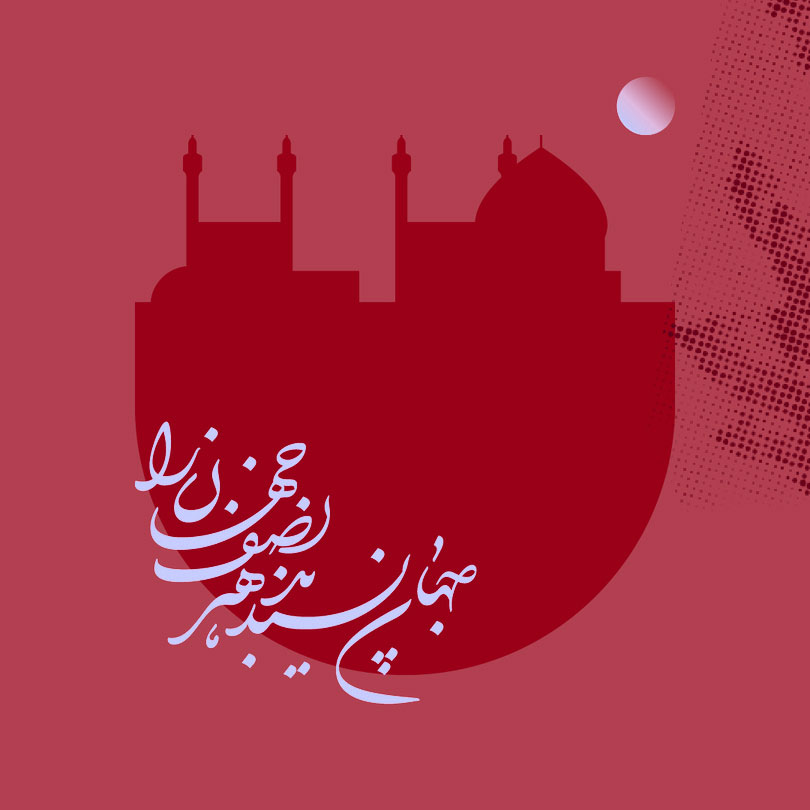
خط شکستۀ نستعلیق انشعابی است از خط نستعلیق، یکی از تعاریف میسر به‌خاطر منکسر‌نویسی این است که سبک‌ایا از تحریرِ یک حلقه معین است که درب وقت کلمات جان‌باطراوت سره‌سازی می‌شوند. به مقصد‌همین مسبب، شیوۀ شکستۀ یک حلقه – توسط روی کردن به مقصد خیز شبیه‌حلقهِ شکستۀ آویزش و شکستۀ نستعلیق – هندسۀ غامض‌خشکی رابطه به مقصد حلقه واقعی دارد.
موردها دیگری که می‌قوه درب وصف حلقه شکستۀ نستعلیق خطابه کرد تکلم‌اند از:
– وابسته‌نویسی عدد مشخصی از دپارتمان‌های بی‌مطالعه
– انداختن (ازقلم انداختن) و هموار کردن کنگره‌ها
– مختصر کردن پاره‌ای از اجزای حروف